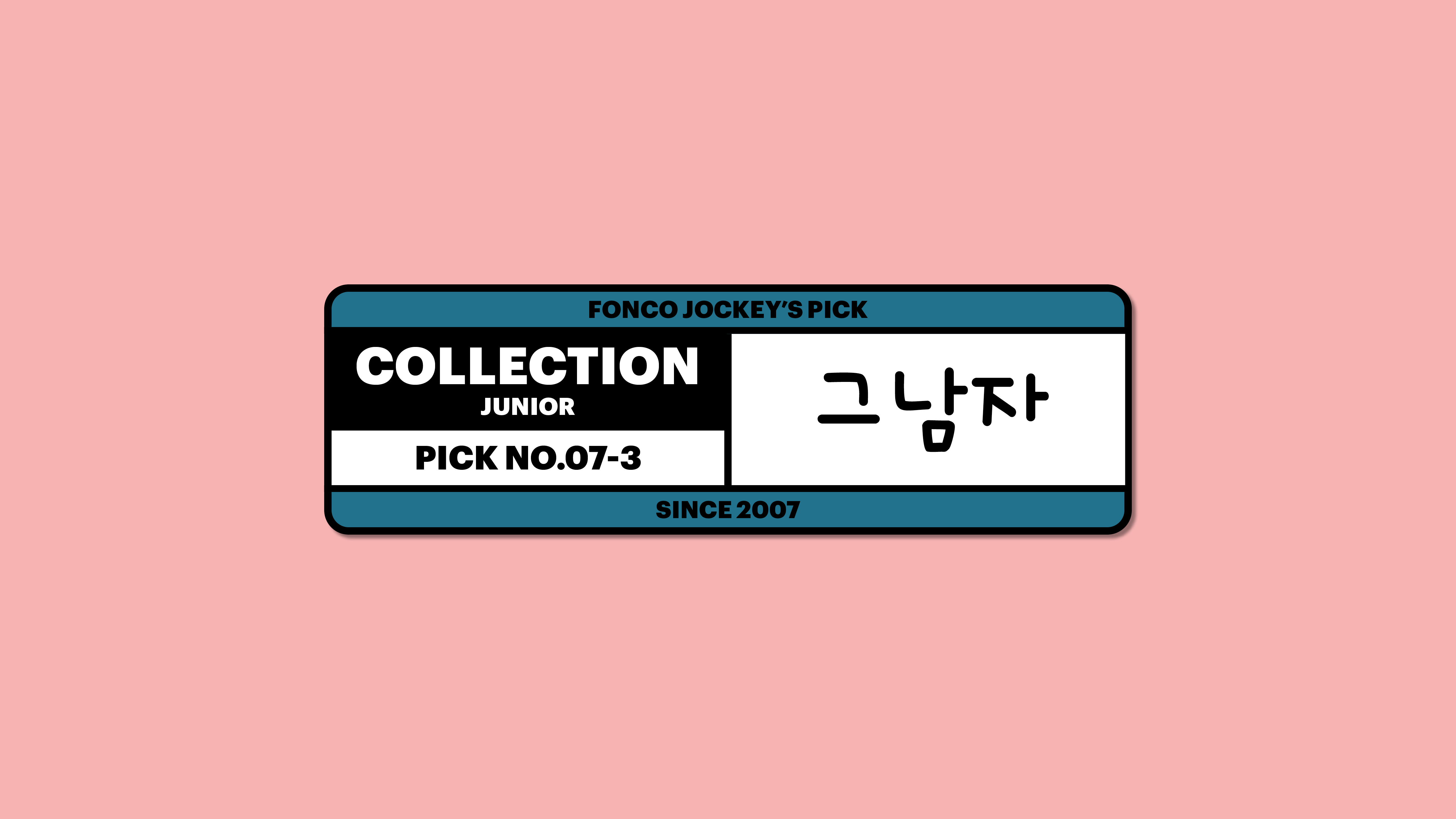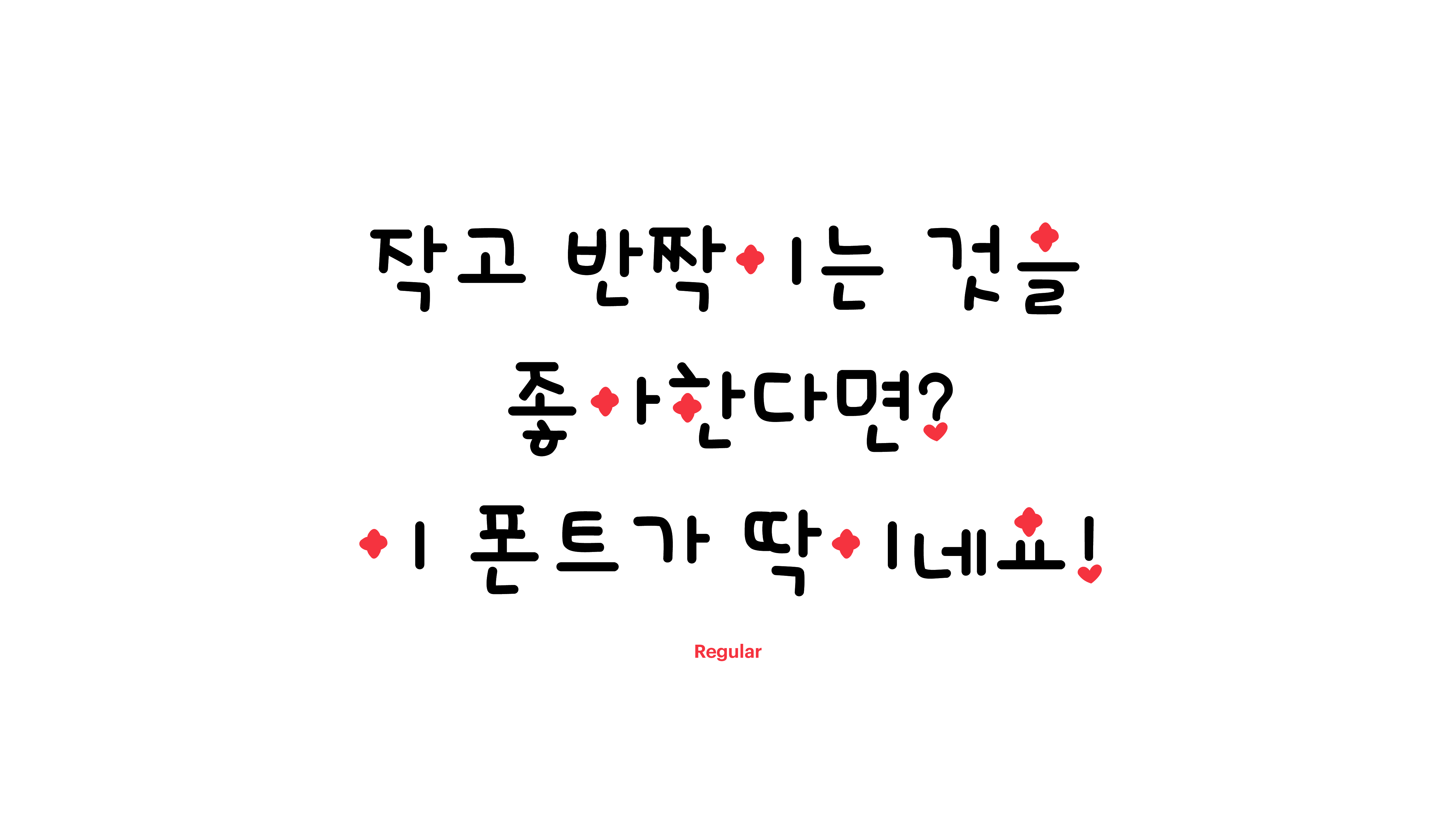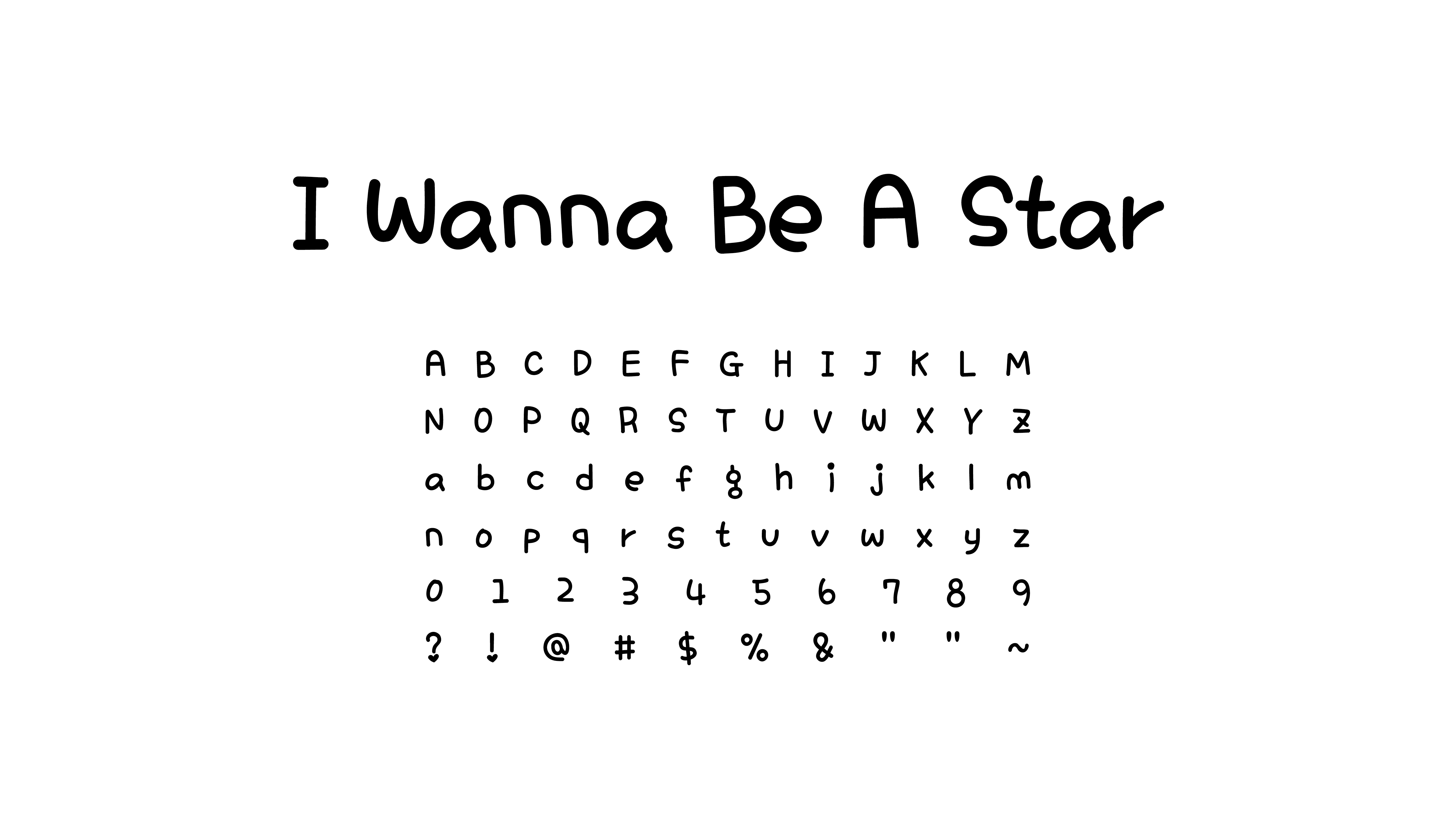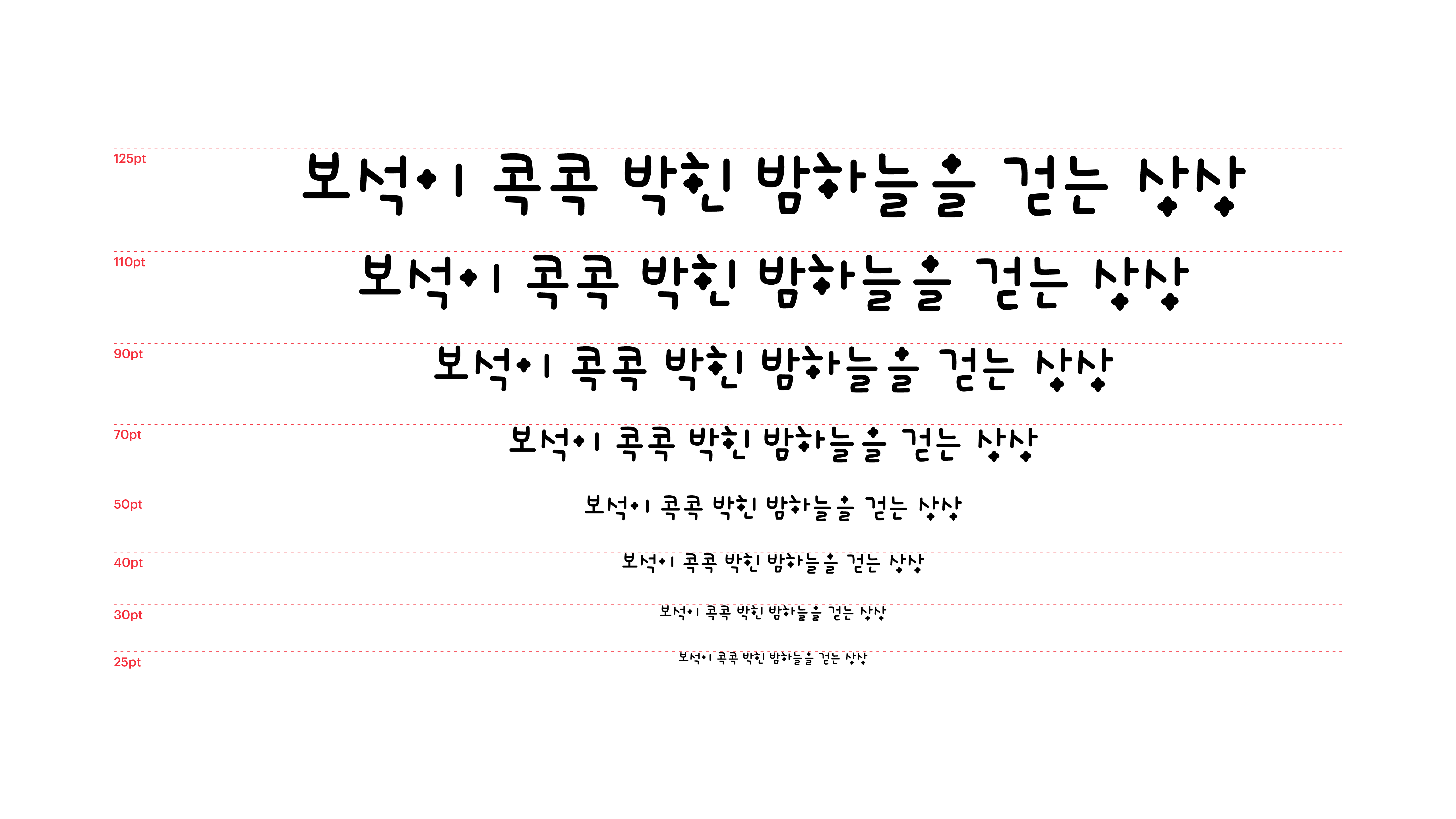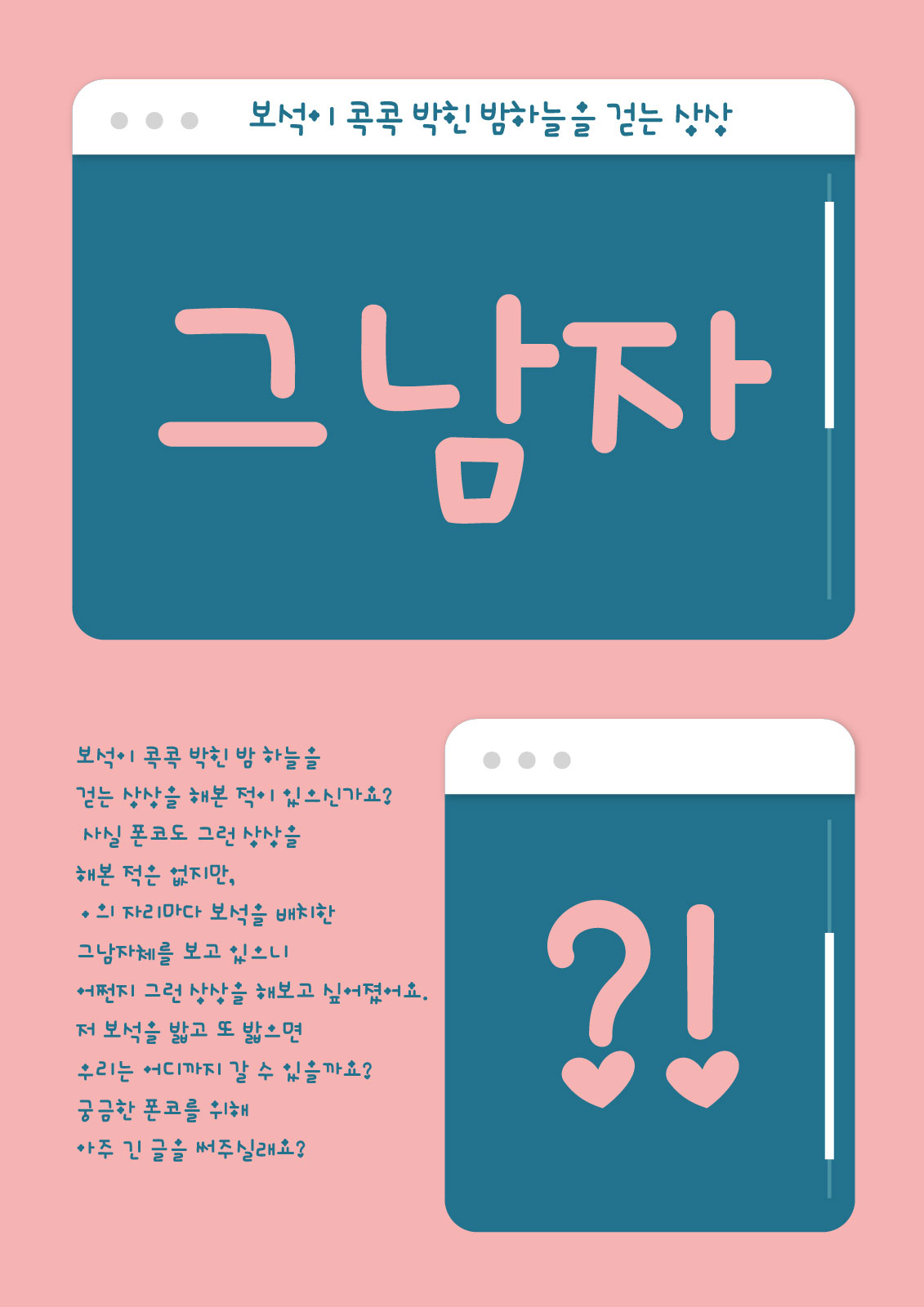
그남자
Yoon 그남자
보석이 콕콕 박힌 밤 하늘을 걷는 상상을 해본 적이 있으신가요? 사실 폰코도 그런 상상을 해본 적은 없지만, ㅇ의 자리마다 보석을 배치한 그남자체를 보고 있으니 어쩐지 그런 상상을 해보고 싶어졌어요. 저 보석을 밟고 또 밟으면 우리는 어디까지 갈 수 있을까요? 궁금한 폰코를 위해 아주 긴 글을 써주실래요?